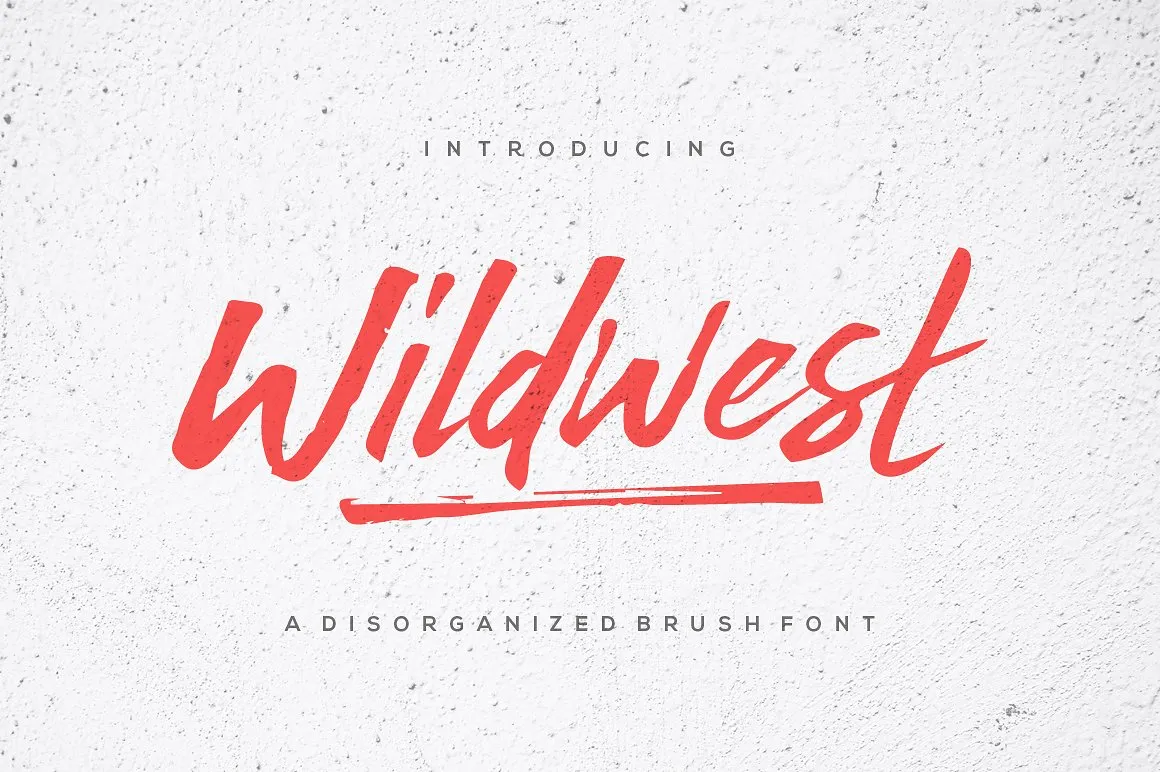
Wildwest Brush Font – Download Grátis
Introduzimos a Wildwest Brush Font! Desenhada pelo designer trustha, esta é uma font premium disponível na Creativemarket. No entanto, estamos lançando-a como gratuita para download hoje. A Wildwest é uma fonte de pincel, perfeita tanto para logotipos quanto para cabeçalhos de websites e rótulos fashion. É também excelente para nome tags, citações, etiquetas em camisetas ou embalagens, entre outros usos. Se você está procurando por um script que se destaque em qualquer projeto visual, a Wildwest é uma escolha ótima. Esta fonte de pincel vai dar ao seu design um toque único e moderno, tornando-a ainda mais atrativa.